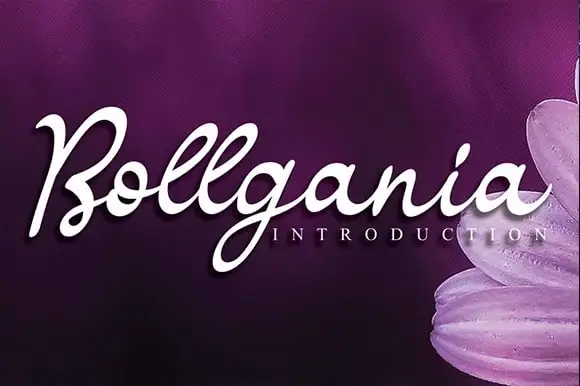
Bollgania Script Font – Download Grátis
A Bollgania Script Font é uma criação exuberante e sofisticada que traz a arte da escrita à vida das mais diversas aplicações digitais. Desenvolvida pelo designer andikastudio, essa fonte de estilo calligrafia oferece um toque refinado e único para qualquer projeto onde seja necessária uma escrita autêntica. Suas linhas fluidas e traços delicados permitem que designers criativos atuem em vários ambientes, desde o uso revigorante em aplicações de mídia social como posts e logotipos, até a utilidade na criação de embalagens, designs de produtos, etiquetas, fotografias ou até mesmo marcas digitais. A Bollgania Script é uma escolha perfeita para aquelas pessoas que buscam dar um toque especial em seus projetos, seja para anúncios, material de escritório ou qualquer projeto que exige a presença de uma escrita que reflete personalidade e bom gosto.